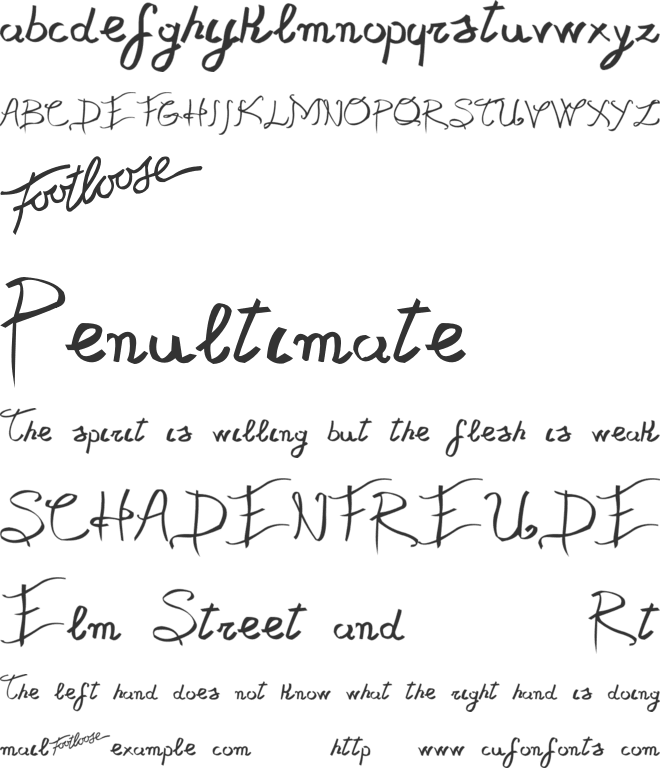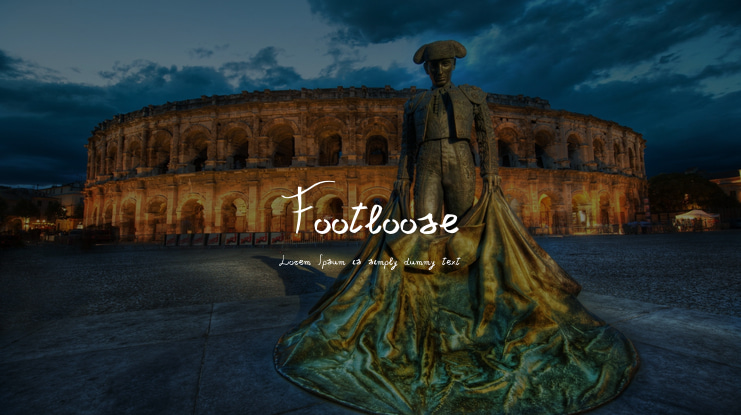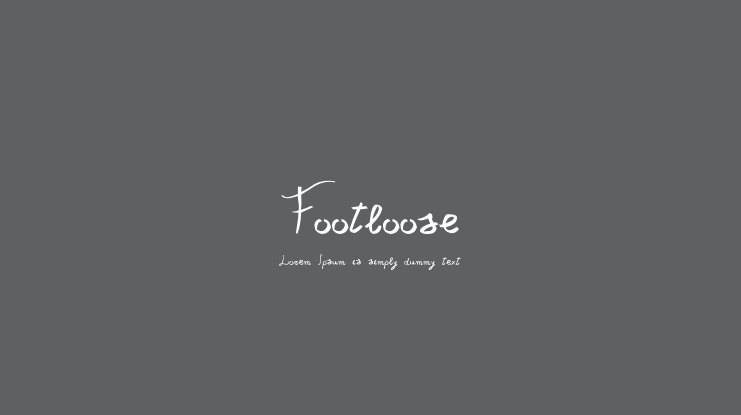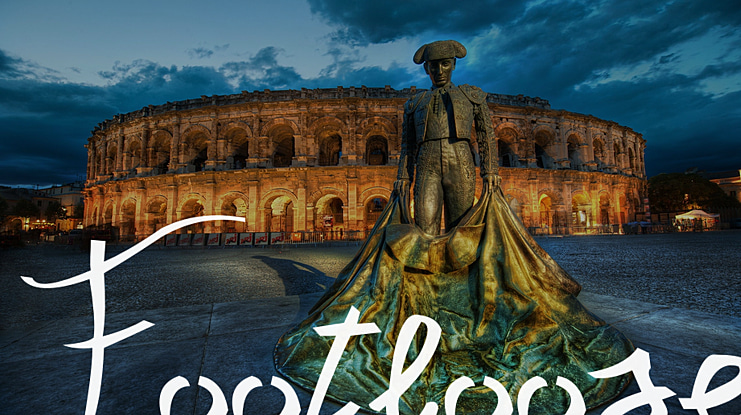
Footloose Font
P.A.Vannucci
Direttamente dal film diretto da Herbert Ross e interpretato da Kevin Bacon, il font inedito per tutti gli estimatori del film.